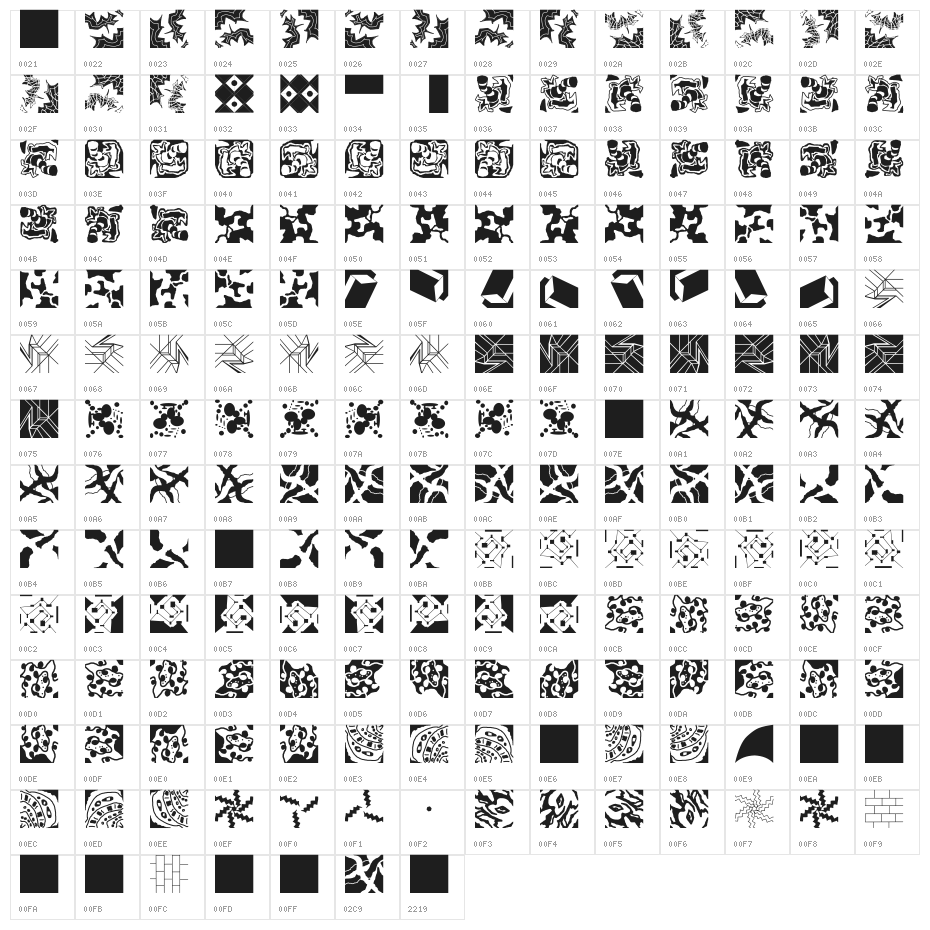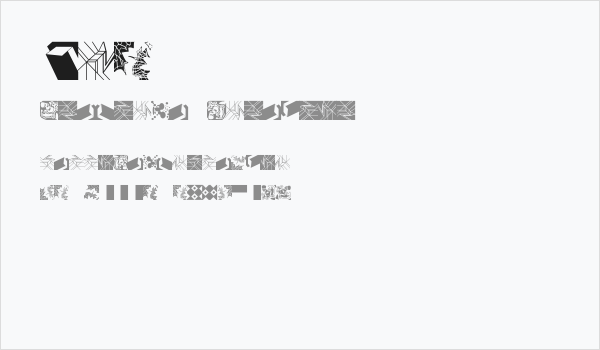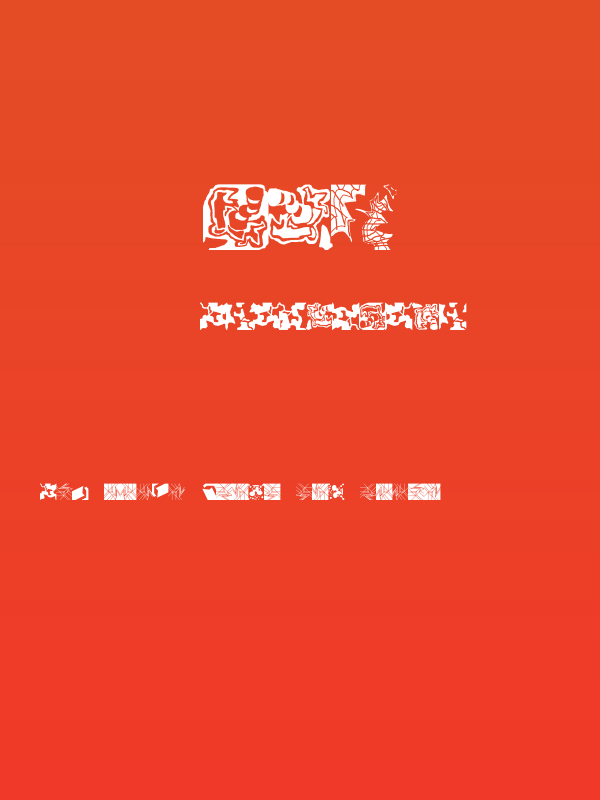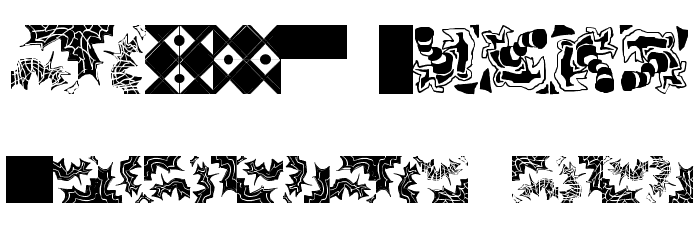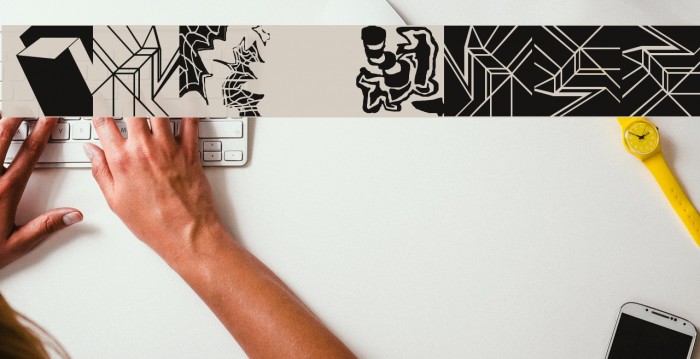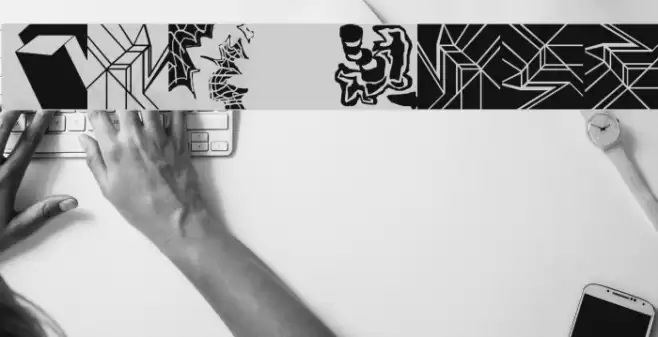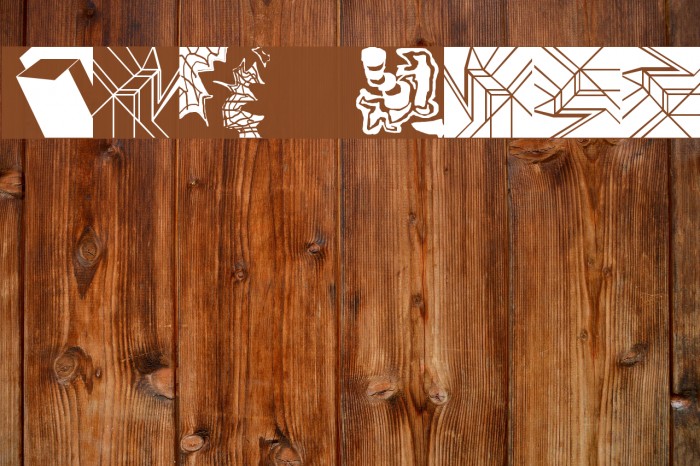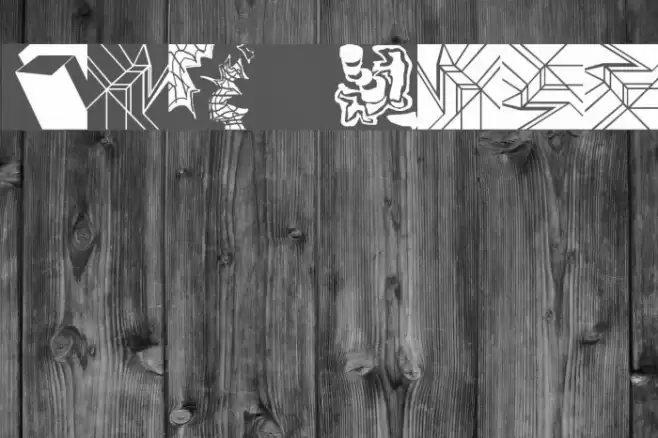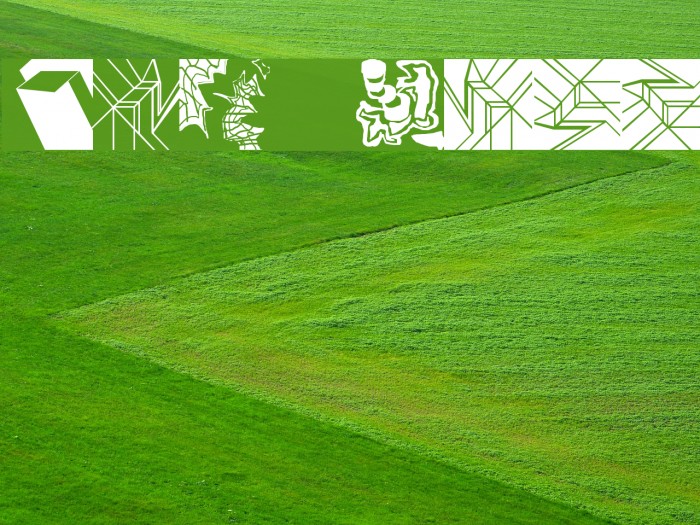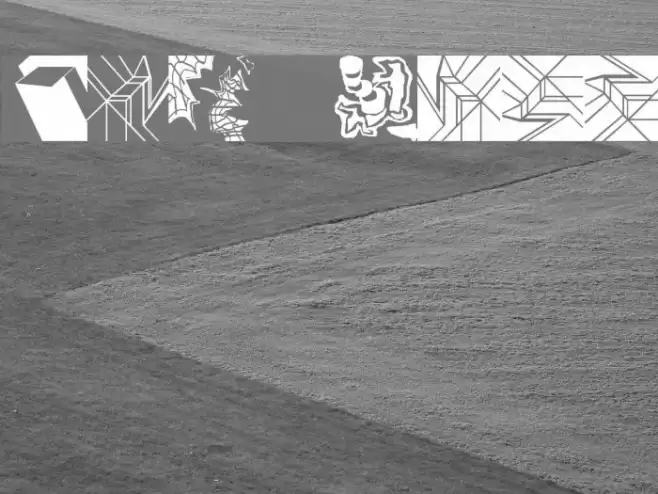
bk1 Font
| Gesamtstil | Modern, Avant-garde |
| Anwendungsfall | Logos, Posters, Artistic projects |
| Vorgeschlagene Projekte | Ideal for artistic projects, album covers, posters, and any design work that benefits from a bold, abstract aesthetic. |